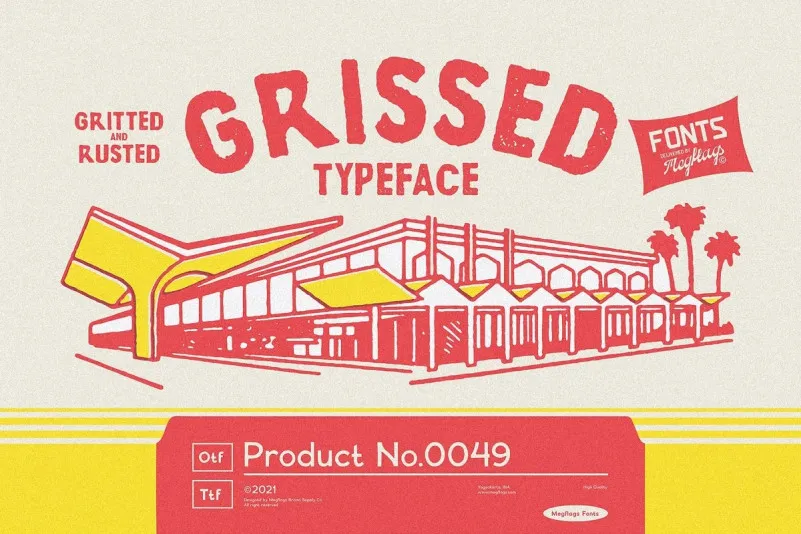
Grissed Font – Download Grátis
A Grissed é uma fonte display que traz ao seu projeto um toque vintage e único. Inspirada nos anúncios de loja antigas, na papelaria vintage e nas linhas de propaganda clássicas, esta fonte vem com duas estilos: regular e obliquo. Cada linha da Grissed é desenhada à mão, garantindo um acabamento distintivo que se alinha perfeitamente ao seu design ou marca. Perfeita para aplicação em logomarcas, embalagens, materiais promocionais, panfletos, banners e até mesmo na criação de camisetas e produtos personalizados, a Grissed traz um toque vintage que definitivamente destacará seus designs. Uma escolha perfeita para quem procura uma fonte display com estilo único e presença.